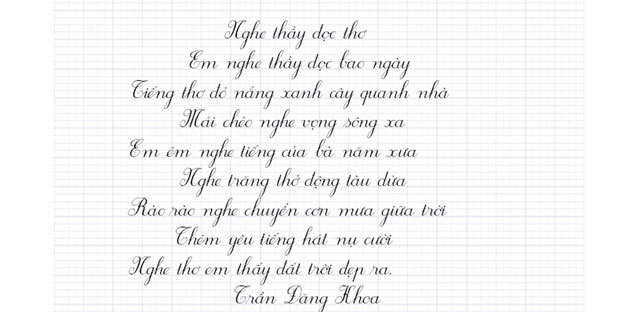
Font chữ tiểu học là bộ công cụ quan trọng giúp mô phỏng chính xác nét chữ viết tay của học sinh trên nền giấy tập tô. Việc tải font chữ tiểu học chuẩn mực giúp giáo viên, phụ huynh và các đơn vị giáo dục dễ dàng soạn thảo giáo án, bài tập luyện chữ hoặc thiết kế các ấn phẩm trang trí góc học tập.
Đặc điểm của bộ font chữ tiểu học chuẩn trong soạn thảo
Điểm khác biệt rõ rệt của dòng phông này chính là cấu trúc nét chữ mô phỏng hoàn thiện theo quy định của ngành giáo dục. Các mẫu tải font chữ viết tay tiểu học thường sở hữu những đường nét thanh mảnh, uốn lượn tự nhiên, giúp trẻ dễ dàng nhận diện mặt chữ và làm quen với kỹ thuật đưa bút. Đặc biệt, bộ font này có khả năng hiển thị các dòng kẻ ô ly (4 ô ly hoặc 5 ô ly) ngay trong văn bản, tạo ra một môi trường luyện tập trực quan giống hệt như trên vở viết thực tế.
Sự ổn định về mặt kỹ thuật của phông chữ tiểu học còn nằm ở tính tương thích cao với các phần mềm văn phòng. Việc tải font tiểu học chuẩn giúp loại bỏ các hiện tượng lỗi dấu thanh hay sai khoảng cách giữa các ký tự thường gặp ở những bộ font chưa được tinh chỉnh. Đây là phương án hiệu quả để tạo ra những mẫu bài tập tô nét đứt (dot font) hoặc các đoạn văn bản mẫu chữ đứng, chữ nghiêng sắc nét, hỗ trợ tối đa cho quá trình rèn luyện tính kiên trì và sự khéo léo của học sinh.
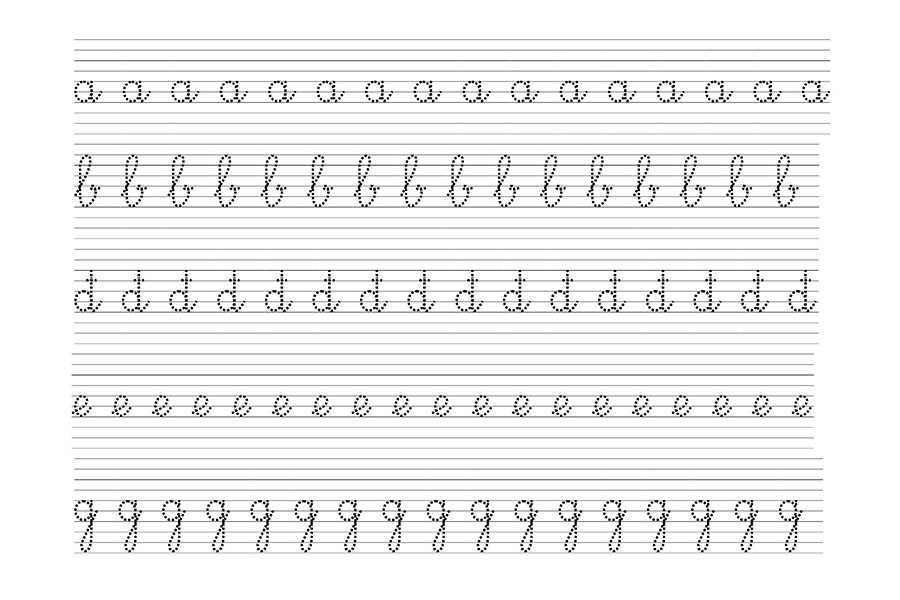
Thông số kỹ thuật và tải font chữ tiểu học tập viết
| Dòng Font tiêu biểu | Đặc tính thiết kế | Ứng dụng phù hợp |
|---|---|---|
| HP001 4 hàng / 5 hàng | Mô phỏng nét bút mực, có ô ly chuẩn | Soạn giáo án, làm bài tập tô |
| VnTimeH / VnClass | Chữ đứng chuẩn mực, dễ đọc | Bảng chữ cái, bảng nội quy lớp |
| Dot Font (Nét đứt) | Nét đứt quãng tinh tế | Học sinh tập đồ theo nét chữ |
| Font chữ nghiêng | Độ nghiêng 15-25 độ chuẩn | Luyện viết chữ đẹp nâng cao |
Tư vấn lựa chọn: Để đạt hiệu quả giáo dục cao, bạn nên tải font chữ tiểu học hp001 4h cho các bài tập viết lớp 1 và lớp 2. Sự phối hợp giữa phông chữ nét liền và nét đứt sẽ giúp trẻ có quy trình học tập từ cơ bản đến nâng cao một cách khoa học và hứng thú hơn.
03 Ứng dụng font tiểu học vào thực tế học tập và thiết kế
Nhờ vẻ ngoài giàu tính thực tiễn, việc sử dụng các mẫu từ bộ tải font chữ tập viết tiểu học mang lại giá trị cao trong khâu giáo dục và trang trí không gian sống:
- Tự thiết kế vở luyện chữ tại nhà: Phụ huynh có thể sử dụng tải font chữ tiểu học 4 ô ly hoặc 5 ô ly để in các đoạn thơ, câu danh ngôn trên nền giấy chuẩn, giúp con em mình có tài liệu rèn chữ riêng biệt theo sở thích.
- Trang trí góc học tập trong nhà lắp ghép: Đối với các không gian sống hiện đại, việc dùng font chữ tiểu học để in decal hoặc làm bảng tên góc học tập giúp không gian trở nên thân thiện, tạo động lực học tập tích cực cho trẻ.
- Hệ thống biển chỉ dẫn mầm non & tiểu học: Những nét chữ tròn trịa, rõ ràng của việc tải font chữ tiểu học chuẩn rất phù hợp để làm biển báo lớp học, khu vui chơi, giúp trẻ nhỏ nhận diện thông tin một cách tự nhiên.
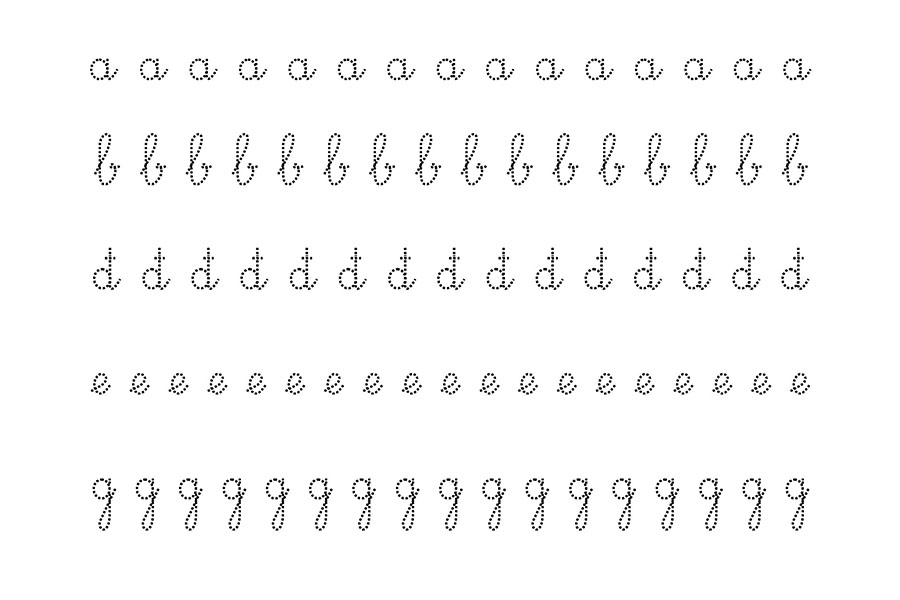
03 lưu ý kỹ thuật khi trình bày font chữ viết tay tiểu học
Để khai thác hiệu quả vẻ đẹp của dòng phông chữ đặc thù này mà không làm rối mắt người xem, người dùng nên lưu tâm một số kinh nghiệm sau:
- Kiểm soát kích thước khi in ấn: Khi tải font chữ tiểu học 5 ô ly, bạn cần thiết lập kích thước chữ trong Word ở mức 14-16pt để các đường kẻ ô ly hiển thị rõ ràng, không bị nhòe nét khi in ra giấy.
- Điều chỉnh khoảng cách dòng (Spacing): Font tiểu học có cấu trúc xếp tầng cao hơn font thông thường. Bạn nên đặt khoảng cách dòng rộng hơn (Line spacing) để các ô ly của dòng trên không đè lên nét chữ của dòng dưới.
- Kiểm tra hiển thị nét đứt: Đối với các phông tập tô, hãy đảm bảo máy in có độ phân giải đủ tốt để các chấm nhỏ li ti không bị biến thành nét liền, giúp học sinh thực hiện thao tác đồ chữ chính xác.